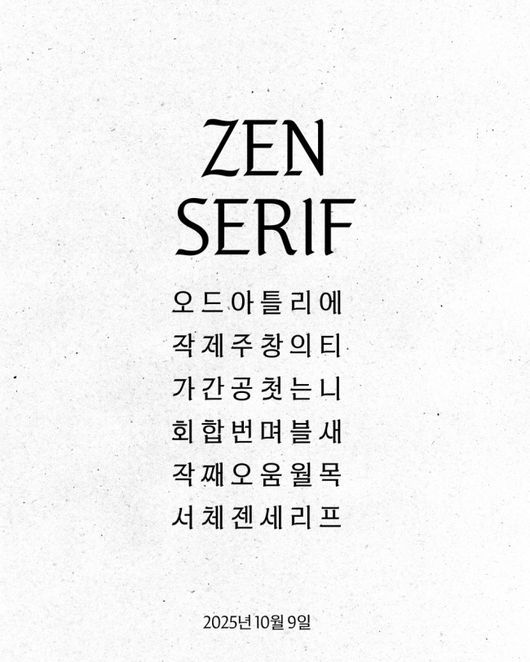
[OSEN=선미경 기자] 그룹 블랙핑크 멤버 제니(JENNIE)가 전통의 미감과 현대적 감각을 담아낸 새로운 한글 폰트로 한국의 아름다움을 알린다.
9일 소속사 OA엔터테인먼트(ODDATELIER)는 공식 홈페이지와 SNS 채널을 통해 더 많은 사람들이 한글을 편리하고 아름답게 사용할 수 있길 바라는 마음을 담은 신규 폰트 ‘ZEN SERIF’(젠 세리프) 출시 소식을 알렸다.
또 OA엔터테인먼트(ODDATELIER)는 메타(Meta)와의 협업을 통해 인스타그램 숏폼 영상 편집 앱 ‘Edits’(에디트)에 한글 폰트를 최초로 등록, 오늘(9일)부터 전세계 모든 앱 사용자가 해당 신규 폰트를 자유롭게 사용할 수 있다.
이번 ‘ZEN SERIF’ 폰트는 전통의 미감과 현대적 감각을 제니와 OA엔터테인먼트(ODDATELIER)의 정체성으로 담아 전 세계에 한글의 아름다움을 알리기 위해 출시된 것으로, 한글날을 맞이해 폰트가 출시돼 더욱 의미가 뜻깊다.
‘ZEN SERIF’는 고정된 이미지를 벗어나 오늘의 시각에서 새롭게 창작된 폰트다. 장식을 최소화해 본질을 살리고, 딱딱한 인상을 덜어내면서 유연한 곡선을 더해 OA엔터테인먼트(ODDATELIER) 특유의 섬세한 예술성을 담았다. 서양의 전통 서체인 블랙레터와 한글을 결합해 누구도 시도하지 않았던 낯선 조합을 완성했다.